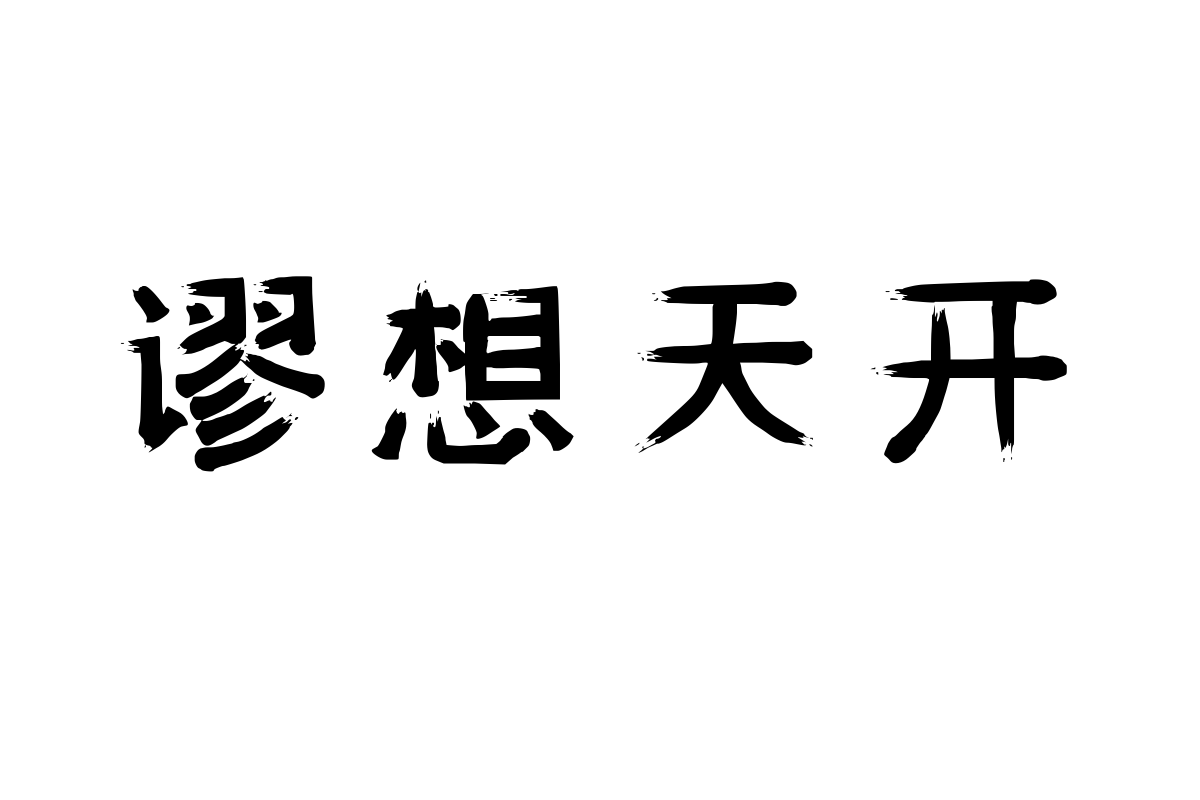
汉标颓废体是一种中文书法字体,它的特点是笔画粗壮,结构松散,给人一种古朴、粗犷的感觉。这种字体在现代设计中被广泛应用,尤其是在广告、包装、海报等领域。
汉标颓废体的特点如下:
1. 笔画粗壮:汉标颓废体的笔画粗细不一,有的笔画比较细,有的笔画比较粗,这种粗细的变化使得字体看起来更加有力量感。
2. 结构松散:汉标颓废体的字形结构比较松散,没有太多的规则和约束,这使得字体看起来更加自由和随意。
3. 古朴粗犷:汉标颓废体带有一种古朴的气息,同时也有一种粗犷的美感,这种风格在现代设计中非常受欢迎。
4. 易于识别:由于汉标颓废体的独特风格,使得它在视觉上具有很强的辨识度,这对于广告和包装等需要突出品牌特色的领域来说是非常有利的。
总的来说,汉标颓废体是一种具有独特风格的中文书法字体,它的粗犷、古朴的风格使得它在现代设计中得到了广泛的应用。